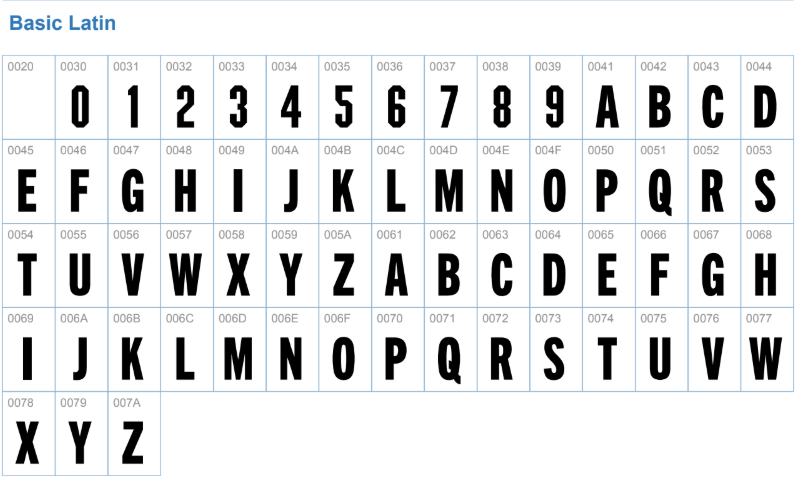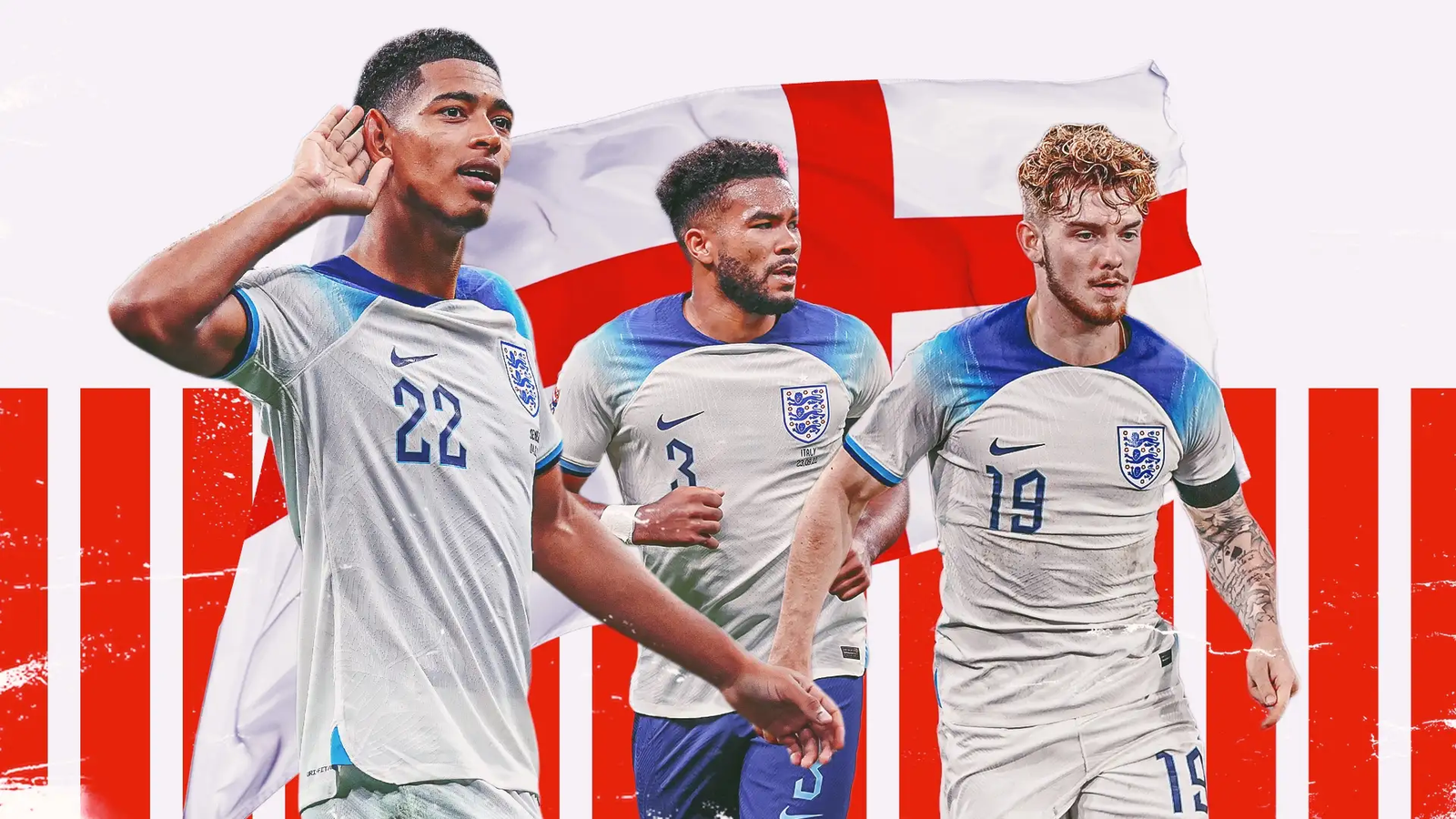
A contagem regressiva para 2026 já começou, e a seleção inglesa entra em campo com uma identidade visual totalmente repaginada. No coração desse projeto está a tipografia oficial, elemento que carrega o peso da tradição dos Três Leões com um toque decididamente contemporâneo.
Para designers, colecionadores e torcedores que acompanham cada detalhe do uniforme, ter acesso ao estilo exato dos números e nomes faz toda a diferença. Seja para personalizar uma camisa, criar uma arte de jogo ou alimentar um projeto gráfico, a fonte da Inglaterra 2026 conecta o digital ao gramado.
Estilo visual da tipografia
A fonte aposta em números com traços retos e terminações levemente angulares, mantendo alta legibilidade mesmo em transmissões de TV e fotos de ação. Há um equilíbrio interessante entre a herança clássica do futebol britânico — lembrando placas de estádios históricos — e a limpeza exigida pelo design esportivo atual.
O “1” aparece sem serifa inferior, o que dá velocidade à leitura. Já o “7” ganha um corte diagonal discreto que remete à precisão tática dentro de campo. Nada de excessos: a tipografia respira modernidade sem perder a solidez.
Aplicação no uniforme
No manto home branco, a fonte aparece em azul royal, com contorno limpo que destaca nome e número mesmo em dias nublados. Para a camisa away vermelha, o texto vem em branco puro, garantindo contraste máximo contra o fundo intenso.
A terceira camisa, num tom fechado de azul petróleo, traz a tipografia em dourado fosco — uma homenagem às conquistas que a Inglaterra espera celebrar em 2026.